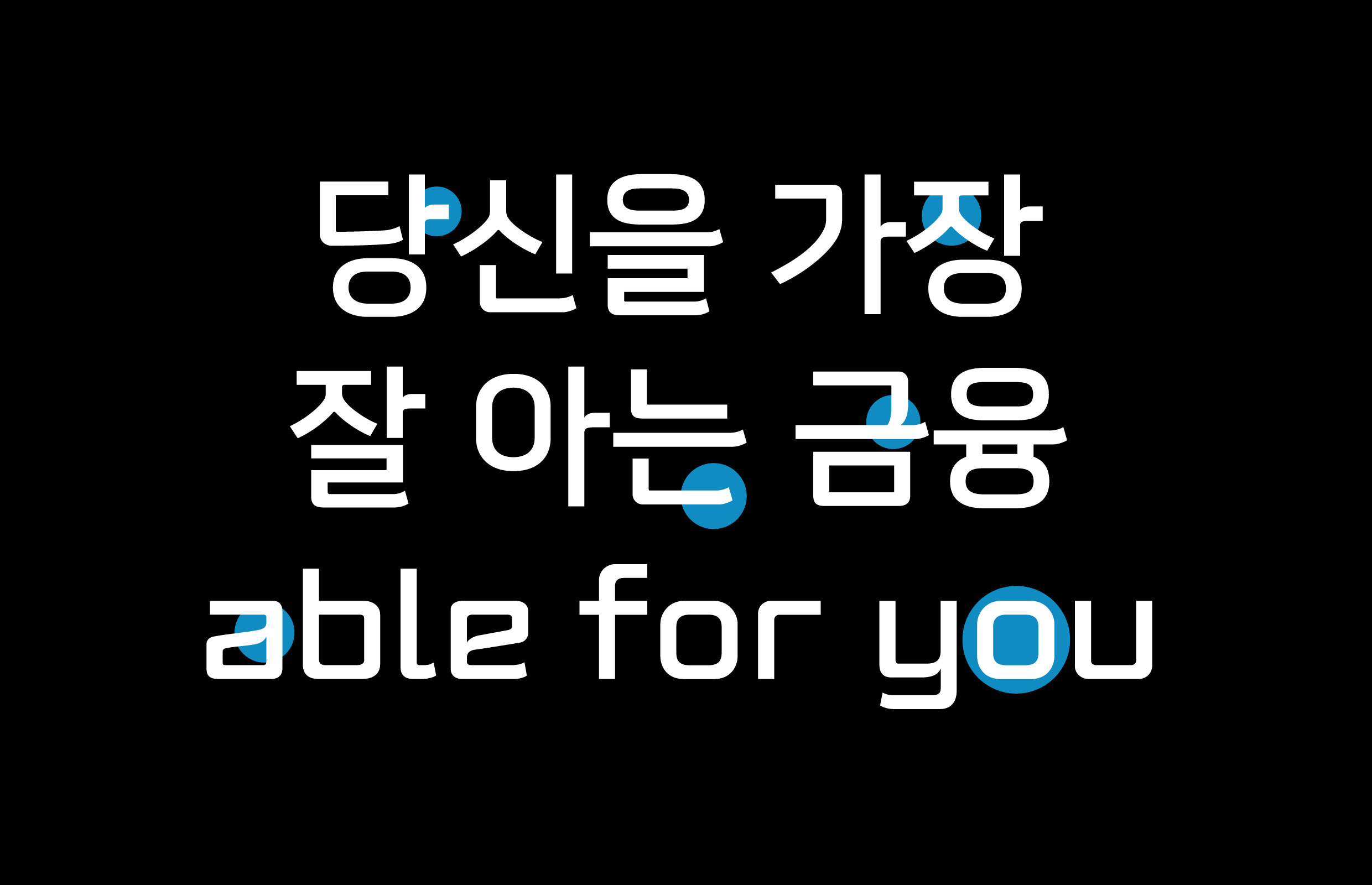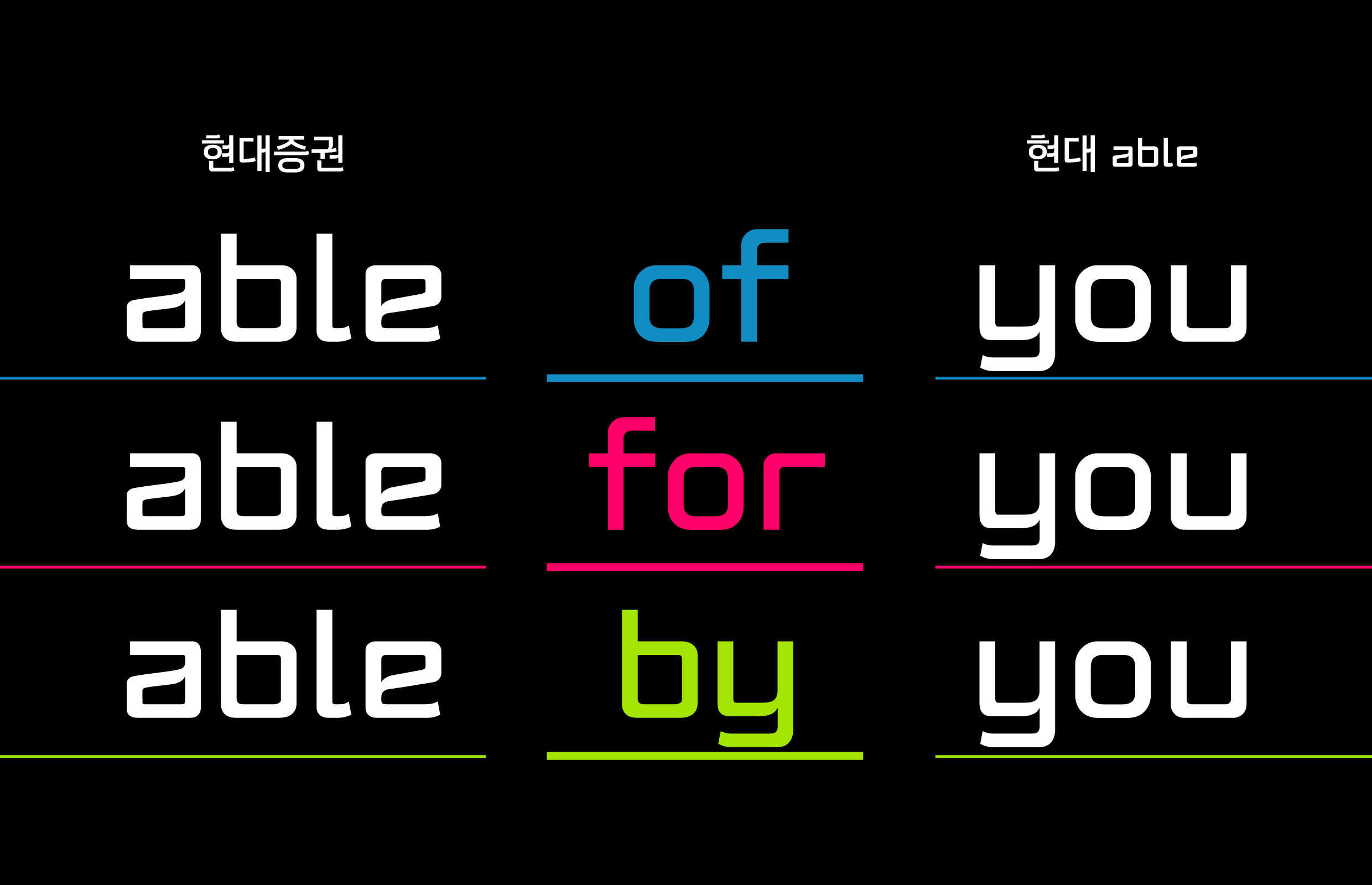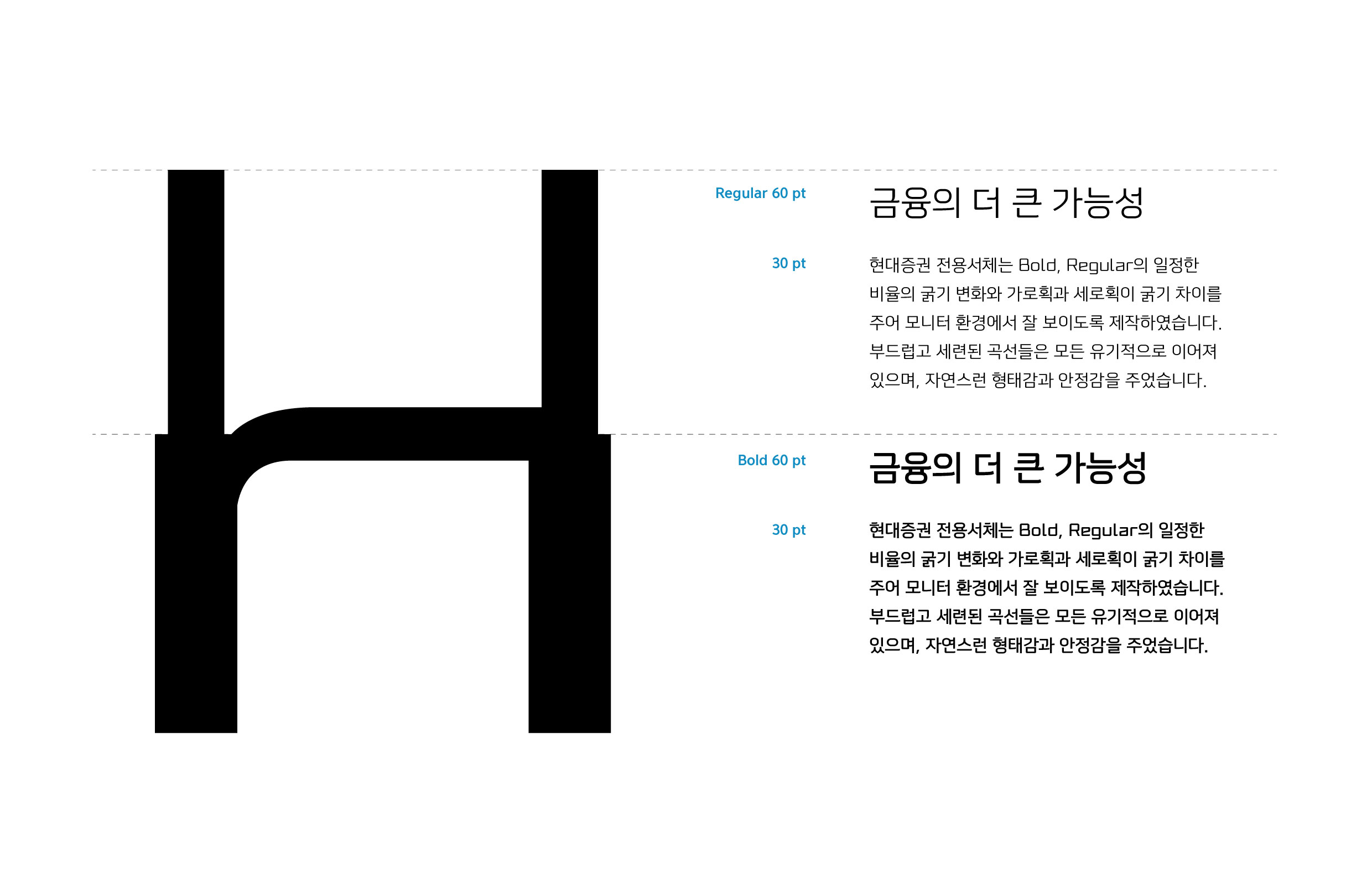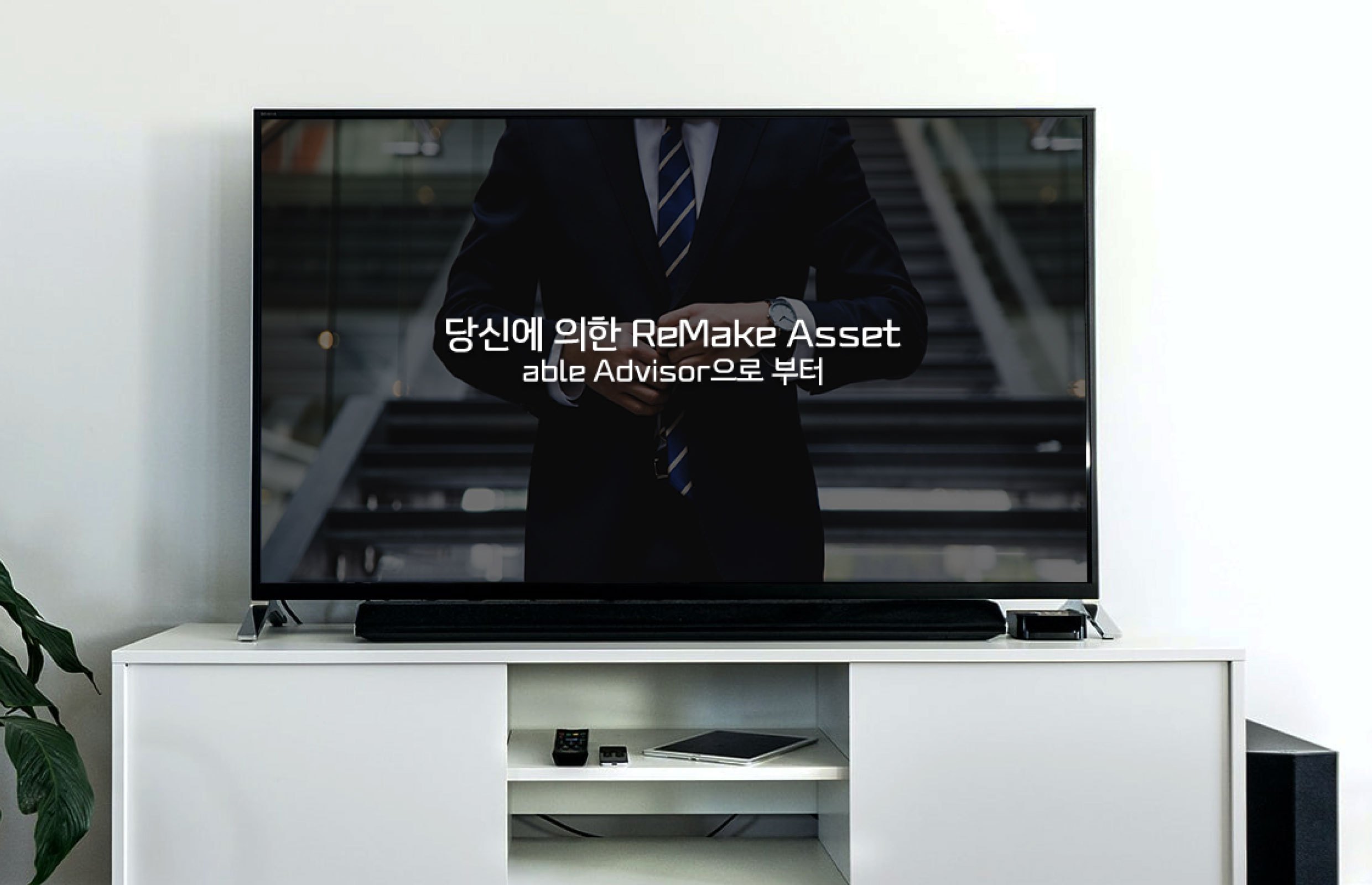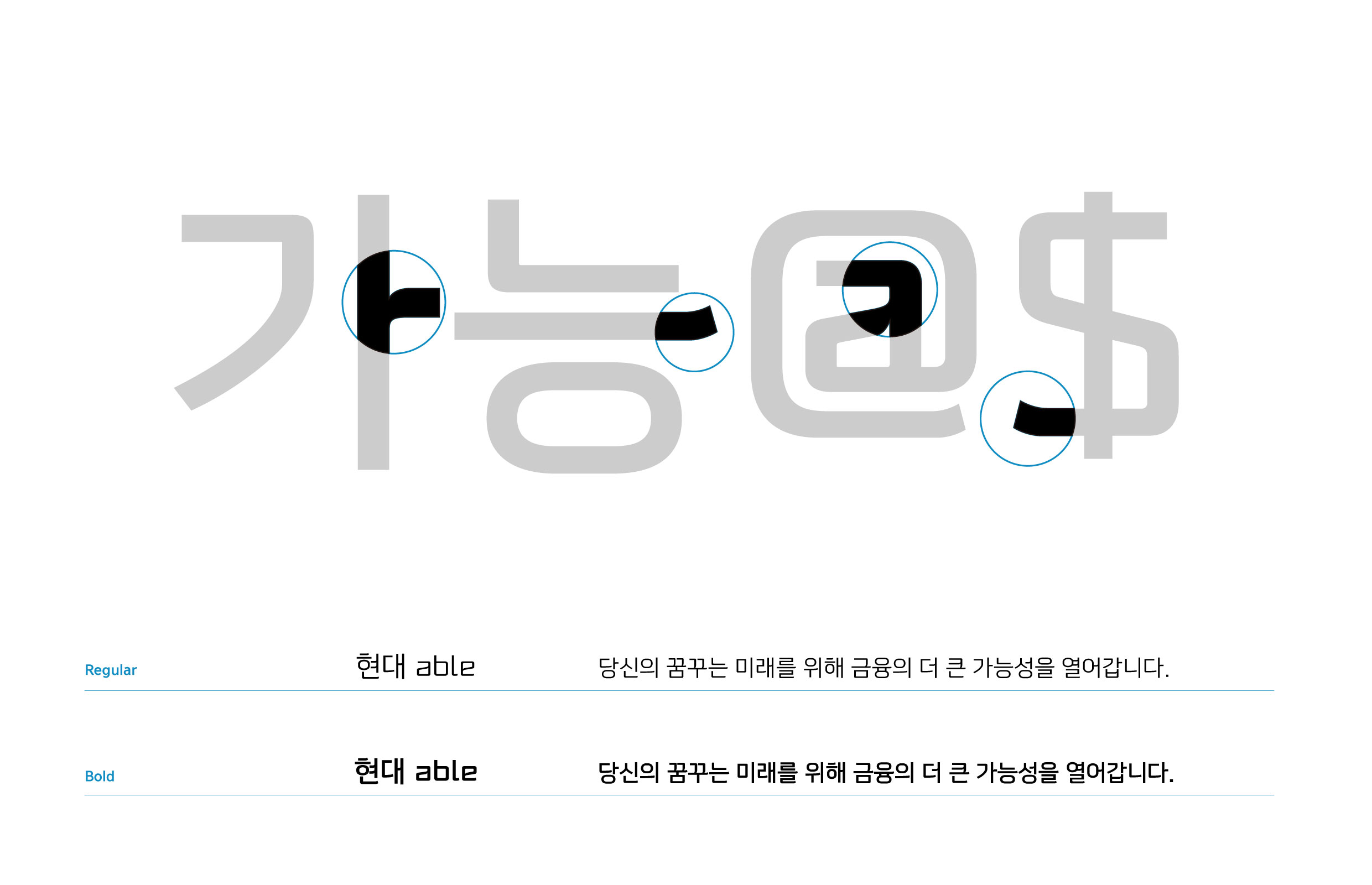
현대증권
현대증권 [현대 able]
증권사 최초의 단독 브랜드 ‘에이블(able)’ 출시와 함께 개발된 전용서체. 변화를 두려워하지 않는 현대증권만의 역동적이고 긍정적인 브랜드 이미지를 글자에 담았다. 라틴 알파벳과 한글이 시각적으로 유기적인 흐름새를 이루는 점이 특징이다.